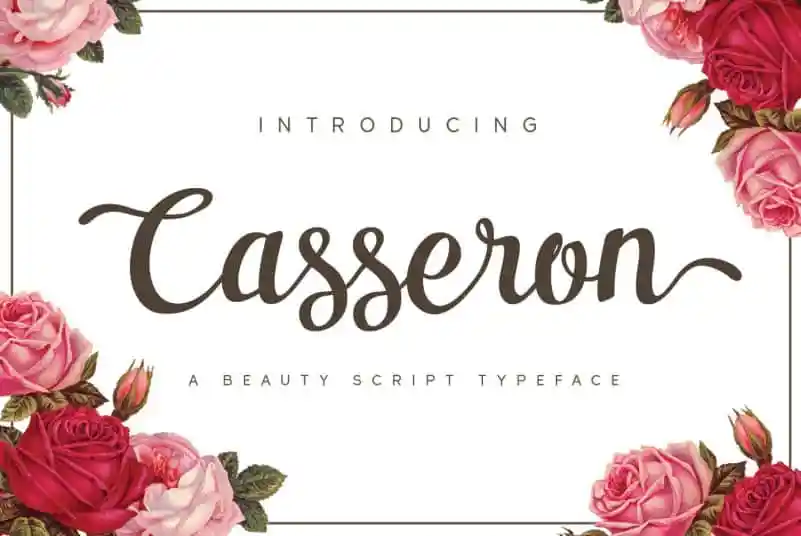
Casseron Script Font
A Casseron Script Font é uma elegante tipografia script com alternativas de caracteres cursivos doces e divertidas. Suas formas fluidas fazem dela uma escolha ideal para projecções de marca, logomarcas, convites de casamento, posts nas redes sociais, anúncios, embalagens de produtos, designs de produtos, rótulos, fotografia e até mesmo as marcas em fotos. Perfeita para qualquer projeto que precise de um toque autêntico do papel da vida. Composta pelo designer Patria Ari Typestudio, essa fonte é uma excelente escolha para aqueles que buscam incorporar personalidade e delicadeza a seus trabalhos digitais. Suas linhas fluidas permitem o uso criativo e inspirador em um amplo espectro de aplicativos gráficos, desde anúncios impressionantes até design de produtos minimalistas. Investir no Casseron Script Font é investir na transformação das suas ideias em arte digital, dando seu trabalho uma personalidade única. Seja para criar logomarcas memoráveis ou apenas uma pequena tag de marca que toque o coração do consumidor, a Casseron Script Font oferece um toque autêntico e encantador a qualquer projeto.